在线下场景中的物料、机具尺寸是依据人体工程学为参考,不同位置、不同距离、不同角度下,物料类型 、版面结构、文字层级、字号、字间距等,都影响着对使用者的信息传递。
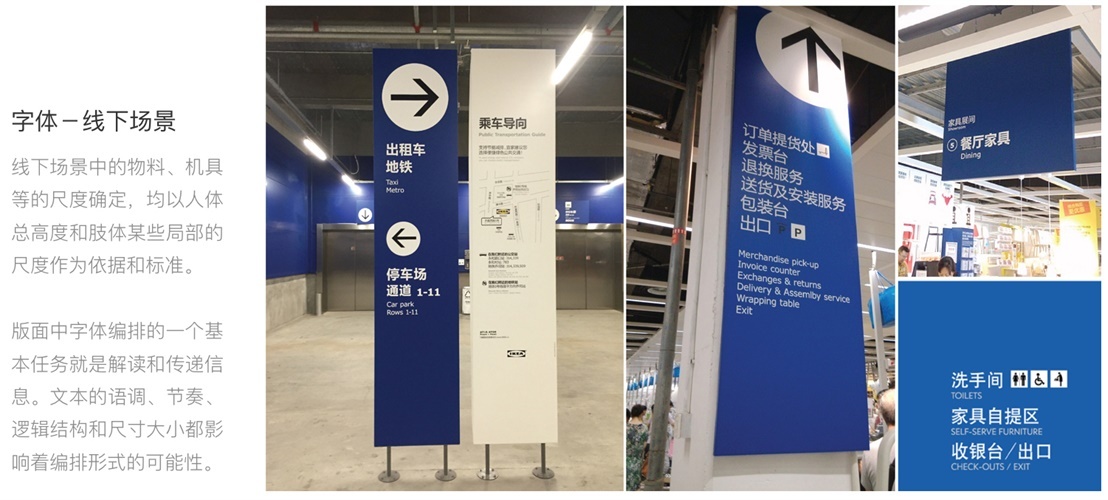
一、原则
1. 动态与静态
人在线下环境对信息内容阅读分为静态与动态。当处于不同的阅读距离时,观看物料的角度也会有所不同。
根据「人体工程学」及「福格行为模型」的数据:当人从动态视距进入到静态视距的红点位置,即人眼看清一个目标并获得视觉印象,平均时间是170毫秒,单个字是250毫秒。
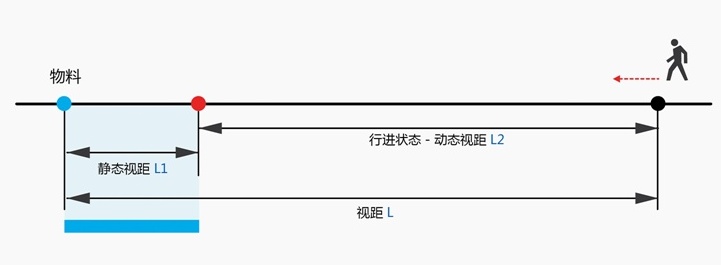
行进速度增加,视角会随增加幅度减小。因此,运动状态下的快速阅读要避免让用户产生「回视」或「眼跳」。
回视:人们在阅读过程中,当碰到不理解的内容时,迅速且无意识地回顾前面的内容。
眼跳:在阅读过程中,眼睛的黄斑中心凹在从一个字移到另一个字时,其眼帘发生的0.1秒突然震颤。
在「动态与静态」原则下,我们需要区分物料与人接收信息的状态和时间,如「远距离+高视角+且多在运动状态下观看的」 大型横幅竖幅就禁止呈现多信息。
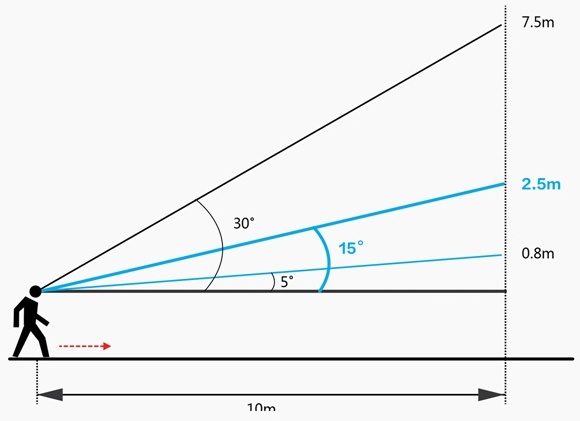
2. 视角与视距
静止状态下,人的水平视觉焦点约介于 3°-10°之间。眼睛最佳转动在水平线以上25°,以下35°左右位置。
在此视圆锥之外的影像(灰色部分)是由周边视觉搜寻,靠余光感受到的区域,其范围介于水平视角以上 60°、以下 70°。
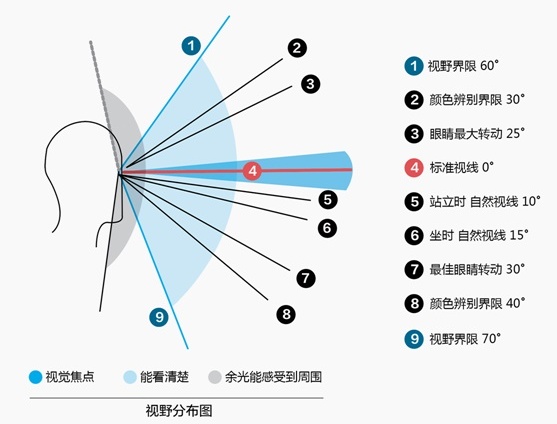
以平均身高1米6的女性用户为例,在其最佳视角下不同视距的三种物料(台卡、海报、易拉宝)传递的信息范围是不一样。当视距为0.5米的情况下,结合前面的「视野分布图」,我们大约可得出其视觉盲区:地平线以上0.35米。
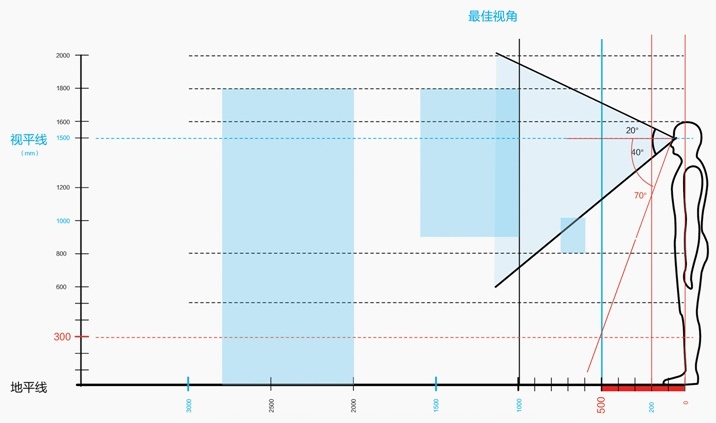
这三种「代表物料」是依据目前支付宝线下各行业线物料分类筛选得出,总体两大类:固定类与移动类,其中固定类中又可细分为5类:地面类、桌面类、墙面类、落地类、悬挂类。
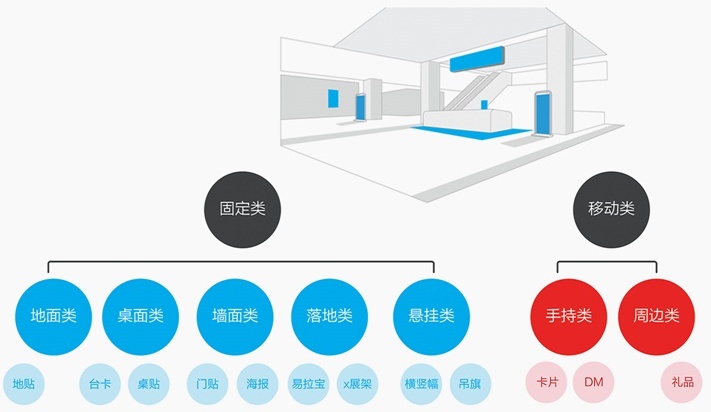
把所有这些物料放入十字象限中,从 「地面」往上到 「桌面 墙面 顶面 」,再看目前聚焦在:桌面类、墙面类、落地类三类物料,而这三类中最具代表的分别是:台卡、海报、易拉宝。所以,后面的「原则&规范 」将重点以这三类为案例做分析。
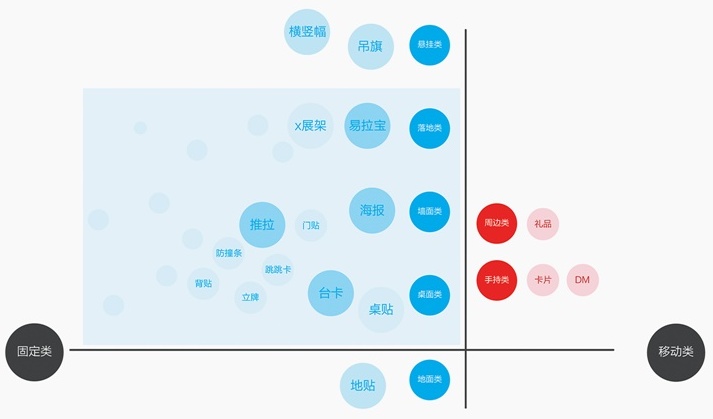
3. 顺序与节奏
从结论-功能-详细说明「倒金字塔型」结构,在线下场景中能短时间内快速、有效的将资讯传达给用户。将资讯群组化,且依重要性程度排序,资讯更易传递。
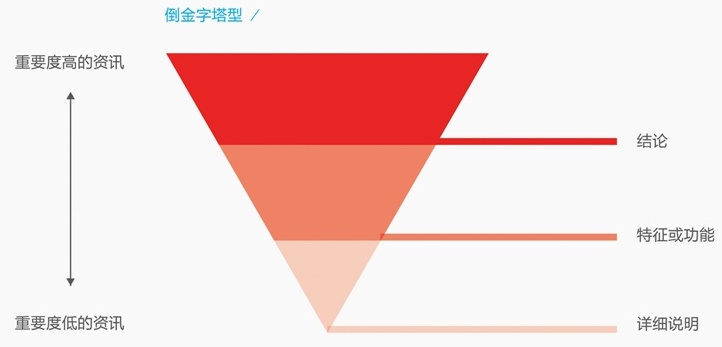
以海报级别的物料为例,其版面应具备三种讯息级别:「最高级别的大标题——中等级别的流程图、功能图——低级别的使用说明 」 按序有节奏的递减;各级别间的差异可能异常明显,主要取决于物料种类(版面大小),某个级别可能非常巨大,而另一个级别可能极其微小。
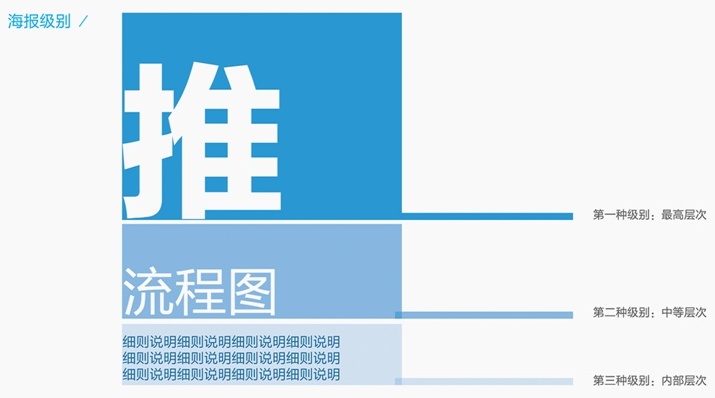
4. 可辨与易读
中英文字体分别是等宽字型和比例字型(文字宽度不同)。比例字型的文字有各自不同宽度,输入时会自动调整字距。因此在编排数字(英文)字体时:
- 不允许用中文字体输入;
- 在相同字号下,数字会比中文小,根据「易读」原则,需调整至高度一致的视觉平衡。
5. 平衡与对比
方正兰亭系列的字体家族至少提供了10种不同字重的字体。我们使用字体家族既可以维持平衡,又可以通过不同字重的强弱关系 ,产生对比强调(对比)的部分与协调(平衡)的部分共存在相同版面中,可使用粗细比例具有共通性「字体家族」。
如图所示,越往上越有明亮、轻快、都会、摩登的感觉,越往下越呈现出稳定说服力、厚重感。
设定不同的文字大小时,若困惑于该呈现多少差距时,可从「等比」、「等差」或「斐波那契」去思考。
这三种对比可以帮助我们去思考该呈现哪种差距的关系,当需要使正副标题具有明确大小差异时 ,可以采用差距最大的「等比数列」。
6. 对齐与留白
文本可以不同的对齐方式来设置:
- 左对齐:以各行的行首对齐
- 右对齐:以各行的行末对齐
- 居中对齐:使轴线位于段落宽度的中间位置
居中对齐后留下的负空间若处理不当,易形成不连续且中断的灰度值外观。因此将文本设置成「两端对齐」能产生整洁、几何形的版式效果。遵循规范二的「字距」或规范七的「图示法」均有助于可规避。
依据前述的线下字体应用的「六大原则」,我们分别细化成:字号、字距、行距、标点等的七条规范。
二、规范
1. 字号
根据「原则一」中提及的人体工程学及福格行为模型的数据,设定可参考数据如下图。
以最常用的几种物料举例:
- 大标题:字号依照文字个数不定,一行标题不超过5个字获取信息最佳;禁止超过9字。
- 内文:手册、单页、DM 的常用字级不小于7.5-9pt;海报的常用字级不小于17-23pt;易拉宝的常用字级不小于24-28pt。
2. 字距
- 中文:当把单字宽度设为一个 a 时,建议字间距的最大极限不要超过1/2a。
- 数字:有些数字的前后会出现「空洞」或「拥挤」的状况,必须以目测方式作适度调整。
- 标点:如「引号」间会有极大空白,破坏整体间隙,亦需按实际情况以目测方式缩小至
视觉协调。
3. 行距
- 内文的最佳行距为字号的1.5-2倍左右。
- 如果物料版面紧张、信息量特别大(如活动规则、说明等),可适当缩小至字号的1.2-1.5倍。
4. 禁则文字符号
- 行头禁则中包括的主要文字与符号:句号、逗号、顿号、连字符、分号、冒号、感叹号、问号、(各种)反括号。
- 分离禁则中包括的主要文字与符号:(各种)正括号。
- 行末禁则中包括的主要文字与符号:两倍破折号、两倍省略号。
5. 跃动比
从字体家族中分别选取字重大且适合阅读的方正兰亭大黑与刊黑、细黑、黑做对比,其跃动比值分别为:
- 黑 vs 大黑:1.83
- 刊黑 vs 大黑:2.95
- 细黑 vs 大黑:2.04
相同字号下的正副标题,采用最佳跃动率为1:2的方正兰亭细黑&方正兰亭大黑;当不同字号时(副标题字号小于正标题),亦可选用方正兰亭准黑(黑)&方正兰亭大黑。
6. 两端对齐
在遵循字号、字间距的基础上,以大标题宽度为基准进行校正。
依照物料种类,海报、易拉宝上大标题(一行)中文字数5字以内最佳;禁止超过9字。
标题在做两端对齐校正时,如已达到「字距」最大极限(规范二),还可加入「图示化」手法(规范七)。
7. 图示化
三种最常用的方式:
- 方式一:把须传达的文字框起来
- 方式二:数字使用英文字体放大表示;整合成单一个体来配置
- 方式三:增加图形符号
呼应 「原则六」中「居中对齐」后的负空间处理,除了「字距调整, 增加图形装饰」等方法调整至「两端对齐」。